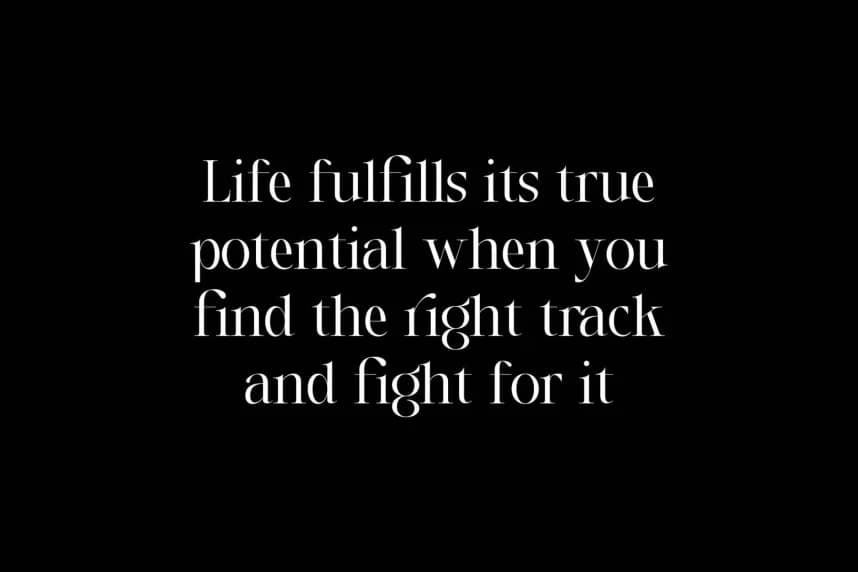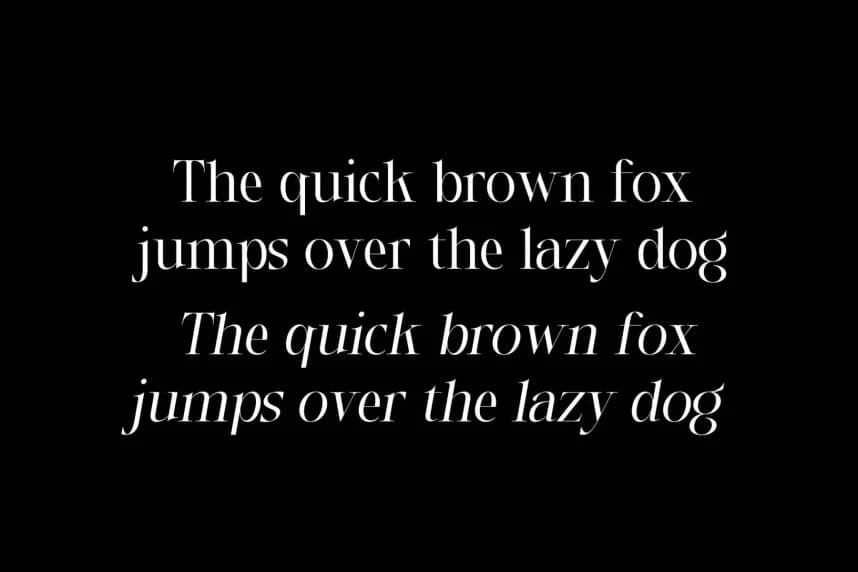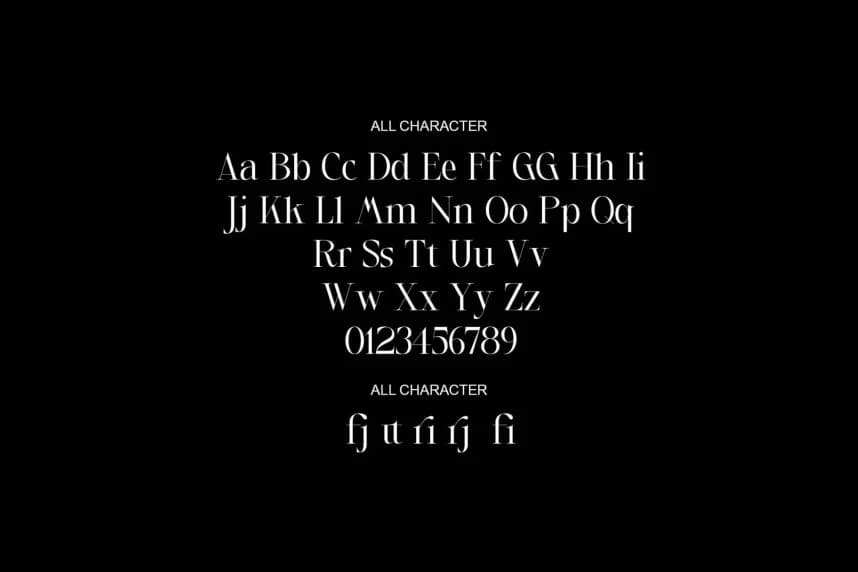
Shader Macalfe Yazı Tipi
Shader Macalife Font, doğal bir stile sahip modern ve harika bir serif yazı tipidir. Bu font mevcut veya klasik tasarımınıza uygundur: İmza. Logo. Markalaşma. Davetiye. Blog Başlığı ve daha fazlası.
Shader Macalife Font, doğal bir stile sahip modern ve harika bir serif yazı tipidir. Bu yazı tipi mevcut veya klasik tasarımınız için uygundur: İmza. Logo. Markalaşma. Davetiye. Blog Başlığı ve çok daha fazlası.